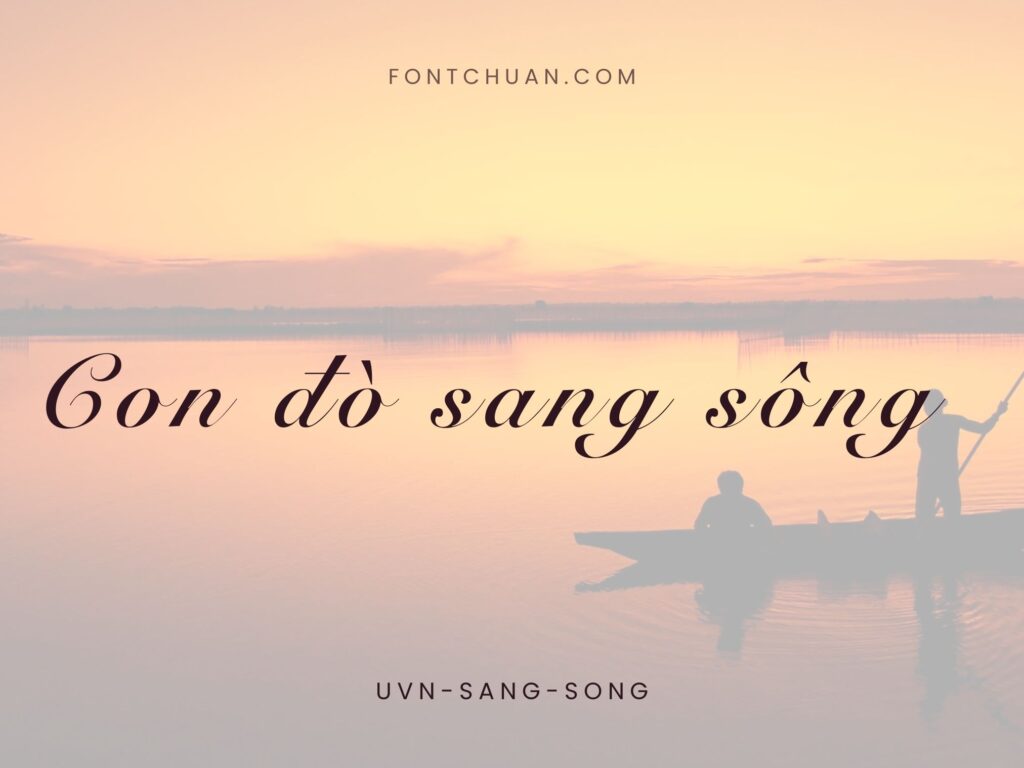
Font UVN Sang Song Việt Hóa
UVN Sang Song là một kiểu chữ script thanh lịch với các đường nét mềm mại và uyển chuyển, tạo cảm giác tinh tế và nghệ thuật. Font này chỉ được sưu tầm và đăng bởi thành viên của Font Chuẩn.
UVN Sang Song có cấu trúc chữ với sự tương phản rõ rệt giữa các nét đậm và mảnh, cùng với các ký tự được trang trí bằng những đường cong duyên dáng. Font này phù hợp cho các ứng dụng như thiết kế thiệp mời, tiêu đề, logo và các ấn phẩm in ấn yêu cầu sự sang trọng và nghệ thuật. Các ngành nghề như quảng cáo, giáo dục, công nghệ và bất động sản có thể tận dụng UVN Sang Song để tạo điểm nhấn độc đáo trong thiết kế.